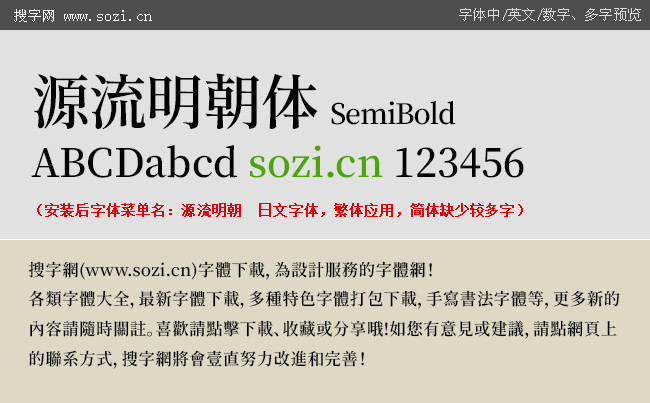
源流明朝SemiBold
搜字網(wǎng)給大家提供一款源流明朝SemiBold中文字體下載,源流明朝體源自思源宋體,風格較原字體改變較大,尤其是勾的筆畫更加具有線條感,使字型看起來更有力道。漢字寬度稍微壓縮,顯得比原始的思源宋體要稍微瘦長。并且在橫筆的起筆與豎筆的起筆、收筆,全都加上粗細變化,仿佛重現(xiàn)鉛字的壓印感,文字較有文學感、人文氣息。適用于大標題、包裝設計、海報設計等應用。